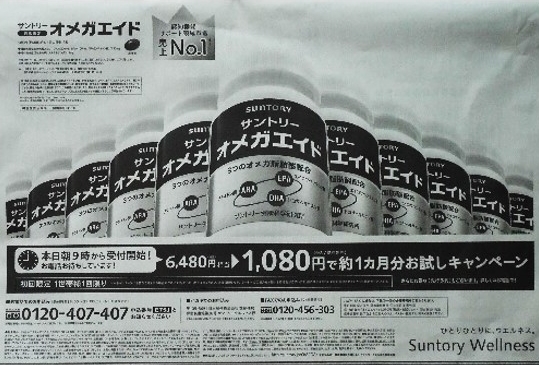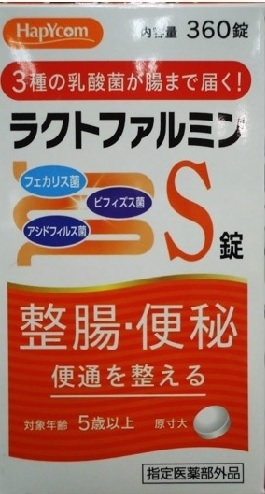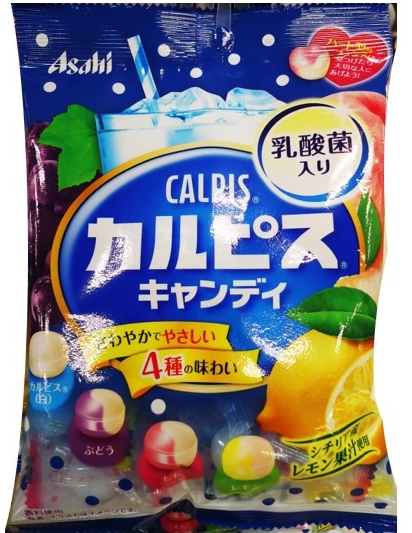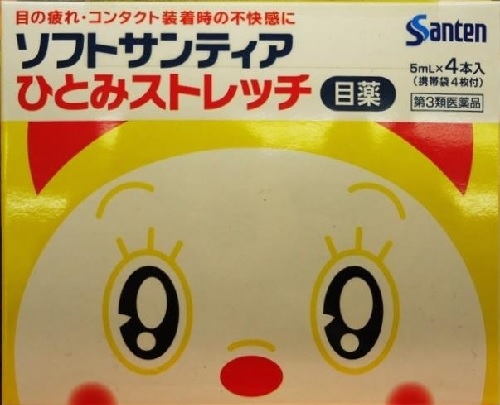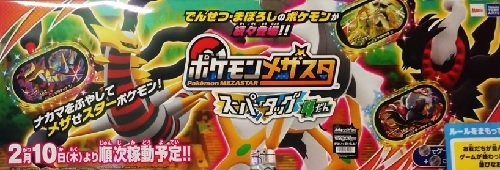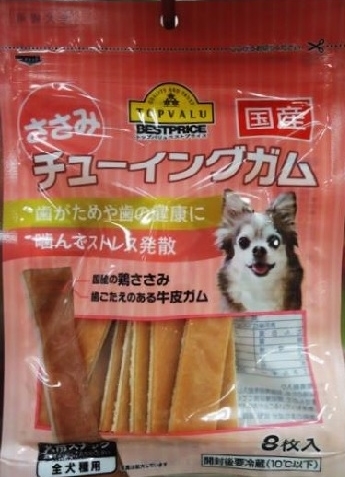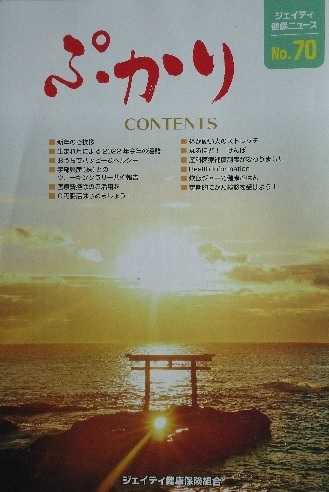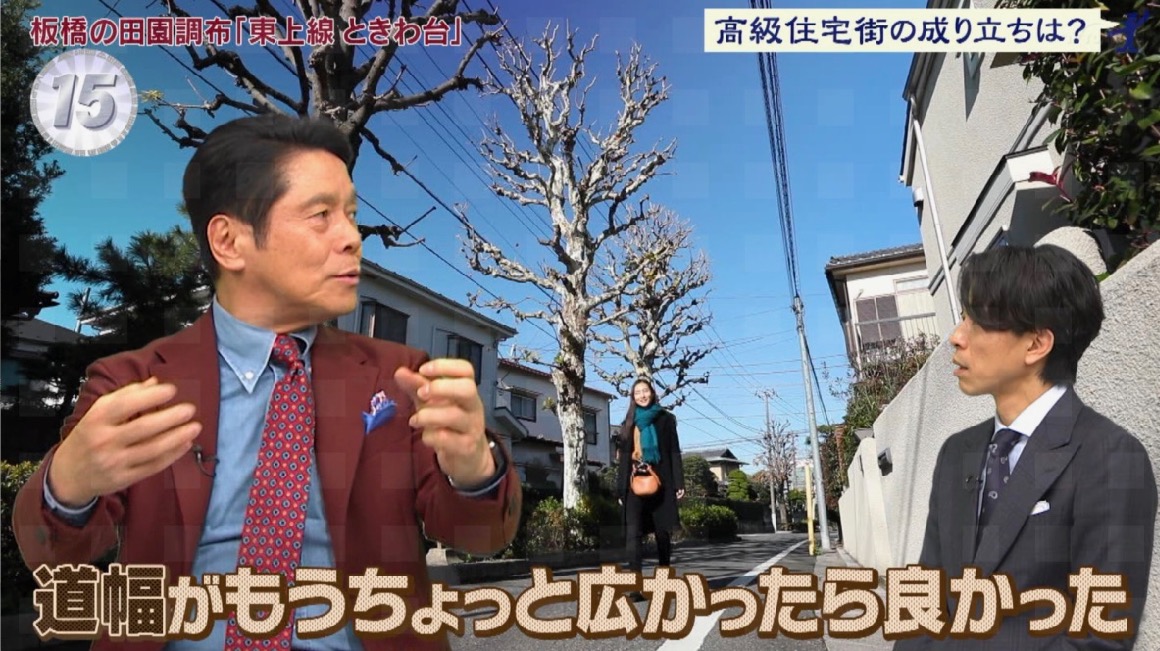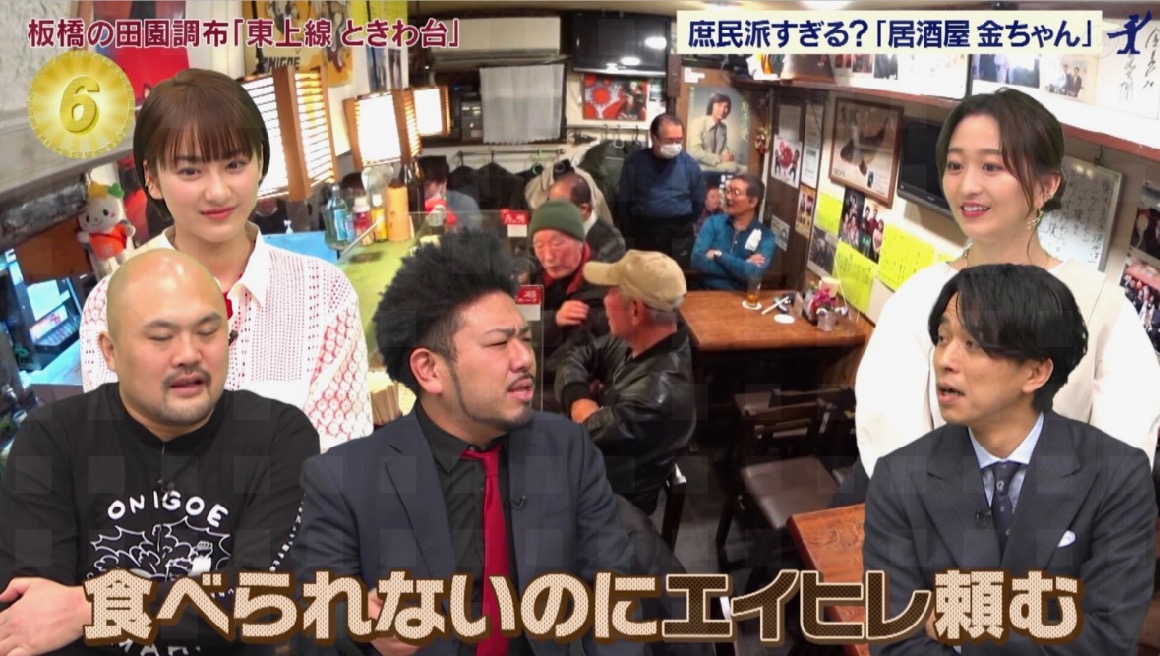
アルコール飲料 さとうゆたか
きのう、桜を楽しみながら飲んだ、ガツーンとサイダーサワー。
イベント案内 大阪のうめ吉
大阪府八尾市ショッピングモールのイベント案内の電子掲示板
3月27日までのバードフェスタの告知
トイレブラシ 大阪のうめ吉
スクラピングバブル 流せるトイレブラシ フローラルソープ
発売 ジョンソン
平野区の薬局チェーン店で
活力系アミノ酸 大阪のうめ吉
活力系アミノ酸BCAAクエン酸
アミノバイタルゼリー リフレッシュチャージ
発売 ajinomoto
平野区の大型薬局チェーン店で
認知症 大阪のうめ吉
医師が発見した 認知症バイバイ
発売 東邦出版
著者 濱崎清利
大阪府八尾市ショッピングモールテナントで
クリアファイル 大阪のうめ吉
電撃クリアファイルマガジン
発売 KADOKAWA
大阪府八尾市のショッピングモールアリオ八尾で
ウソみたいな 大阪のうめ吉
ウソみたいなホントのはなし3
発売 エムデイエムコーポレーション
大阪府八尾市のショッピングモールテナントで
告知板 大阪のうめ吉
サイゼリヤの告知板
大阪府松原市 ショッピングモール
BAKUGAN 大阪のうめ吉
BAKUGANサーベンテーゼ
発売 タカラトミー
大阪市平野区100円ショップで
新聞広告 さとうゆたか
今朝の読売新聞。
国立新美術館のダミアン・ハースト展。
縦画の「音引き」と「ト」には手が加えられている。
こちらはポスター。